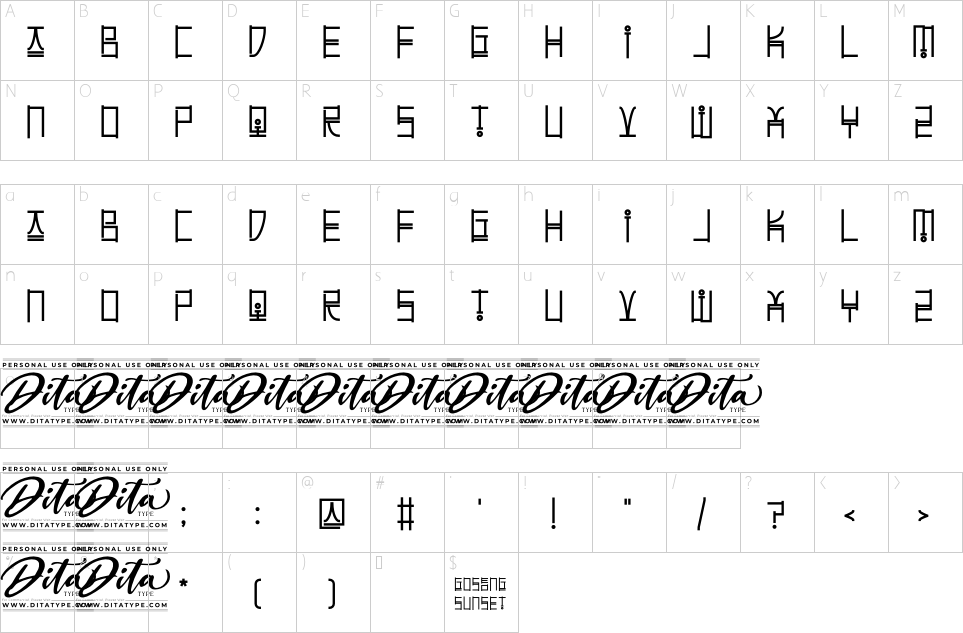
A Goseong Sunset Font é uma elegante escolha para designers amantes de paisagens naturais que valorizam a tranquilidade do pôr do sol. Desenhada pela Dita Type, esta fonte proporciona um toque suave e relajante aos projetos digitais. Com sua inspiração no encantador tomado da cidade sul-coreana de Goseong, a Goseong Sunset oferece linhas delicadas e um tom acalentador que pode trazer uma sensação de calma para qualquer layout ou projeto gráfico. Seja você criando materiais educacionais, arte digital, ou até mesmo letras personalizadas, esta fonte é perfeita para deixar seu trabalho com um toque especial, inspirado na paz e beleza do pôr do sol. Esta fonte está disponível gratuitamente para download tanto no sistema Windows quanto no Mac. Com uma sólida base de usuários que a adquiriram 173 vezes, já se pode perceber o aprecio para este projeto criativo. Seja você um iniciante ou profissional, a Goseong Sunset oferece um toque distintivo e sofisticado sem grandes custos.